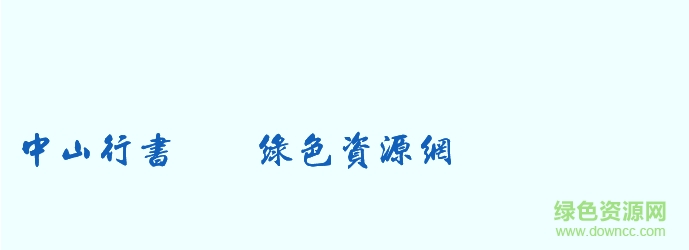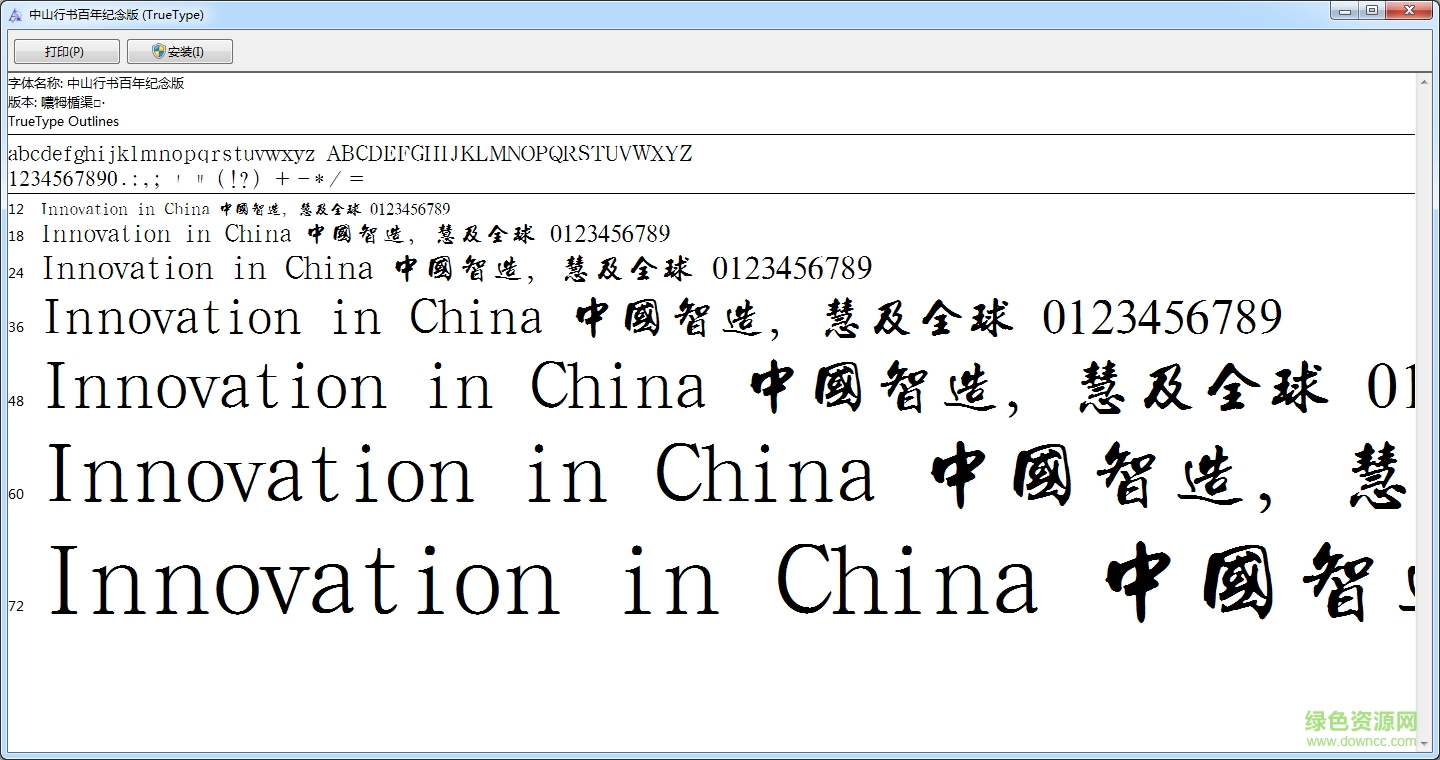
中山行書百年紀(jì)念版是一款具有紀(jì)念性的行書字題,以中國多年的行書為基礎(chǔ)發(fā)展而來,字體雋永簡潔,與孫中山早起字體相符,喜歡這一字體的朋友快來綠色資源網(wǎng)下載吧!
精選國父孫中山手書字跡制成的行書字體,紀(jì)念辛亥革命一百周年所創(chuàng),此款字體字形筆畫均衡,字體緊湊,識別性強(qiáng),端正大方,整體風(fēng)格出色,適用于插畫設(shè)計(jì)、品牌設(shè)計(jì)等方面。